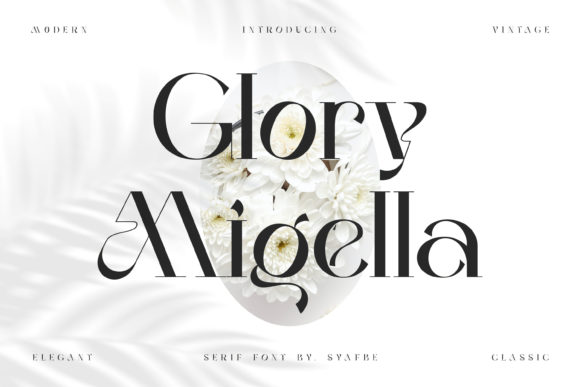
[Creativefabrica] Glory Migella Font (2021)
Название: Glory Migella Font (2021)
Glory Migella
- это классический, шикарный и четкий шрифт с засечками.